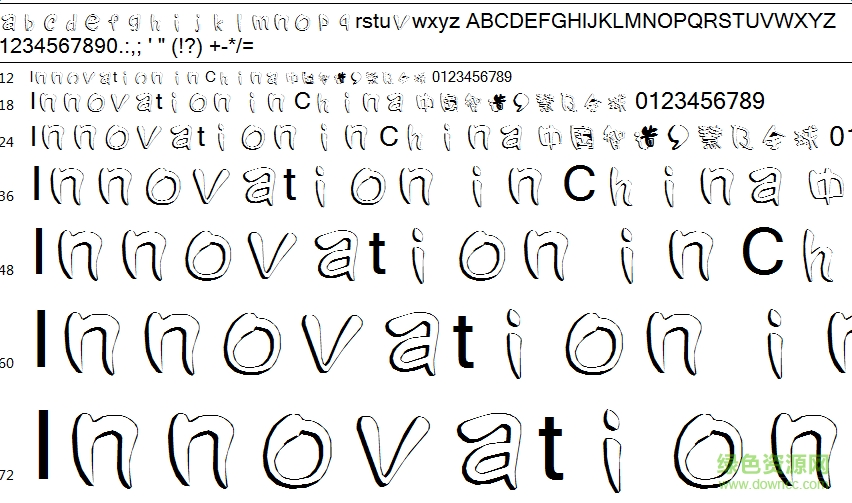
軟件介紹 軟件標(biāo)簽: 其他字體 字體 時裝小立體字體是一款極具個性的炫酷字體,該字體可以廣泛應(yīng)用于橫幅標(biāo)語、美術(shù)設(shè)計、宣傳海報、ppt、影視制作以及內(nèi)容用字等領(lǐng)域,有需要的朋友可以免費下載收藏。字體安裝方法方法一:控制面板/字體/文件/安裝新字體;方法二:直接將字體復(fù)制到C:\WINDOWS\Fonts。方法三:針對win7系統(tǒng),用戶只需選中字體右鍵安裝即可。注意事項本站所有字體資源僅供個人學(xué)習(xí)與參考,如需商業(yè)使用請到相關(guān)官網(wǎng)授權(quán)。 軟件截圖 上一張下一張(1 / 1) 安裝詳細(xì)截圖 猜你喜歡 時裝字體 時裝字體 時裝字體是一種很有特色的電腦字體,不僅寫出來的字形美觀,效果也很不錯,因此使用范圍也比較廣,特別是用于廣告設(shè)計、藝術(shù)設(shè)計等方面都是很不錯的,小編為大家?guī)頃r裝字體大全和打包,歡迎大家來綠色資源網(wǎng)下載使用。 查看更多>> 時裝斑馬魏 10.82M/中文/10.0/下載 時裝滾邊體 11.71M/中文/10.0/下載 時裝毛邊體 24.41M/中文/10.0/下載 時裝豆點細(xì)圓體 3.12M/中文/10.0/下載 時裝扭動體 3.74M/中文/10.0/下載 時裝揪心體 1.91M/中文/10.0/下載 其他版本下載 標(biāo)題 大小 更新日期 下載 下載地址 電腦版 時裝小立體 點擊報錯 軟件無法下載或下載后無法使用,請點擊報錯,謝謝! 關(guān)閉報錯反饋 請描述您所遇到的錯誤,我們將盡快予以修正,謝謝! *必填項,請輸入內(nèi)容 本類最新 dreamweaver字體庫 首爾南山體字體 v1.06 官方版 潮字社風(fēng)云簡ttf 潮字社凌渡鯤鵬簡體字體 潮字社曾玉波手書簡字體 微博慧心字體 相關(guān)文章 Photoshop字體安裝使用方法和技巧 如何解決“無法新增字體”問題 Win 7系統(tǒng)安裝字體方法 網(wǎng)頁字體大小設(shè)置方法 怎么改網(wǎng)頁字體大小 在Linux系統(tǒng)中安裝字體的幾種方法 windows7字體顯示問題:打開某些程序的時候顯示的是亂碼 用戶評論 熱門評論 最新評論 發(fā)表評論 查看所有評論(0) 昵稱: 請不要評論無意義或臟話,我們所有評論會有人工審核. 字?jǐn)?shù): 0/500 (您的評論需要經(jīng)過審核才能顯示)